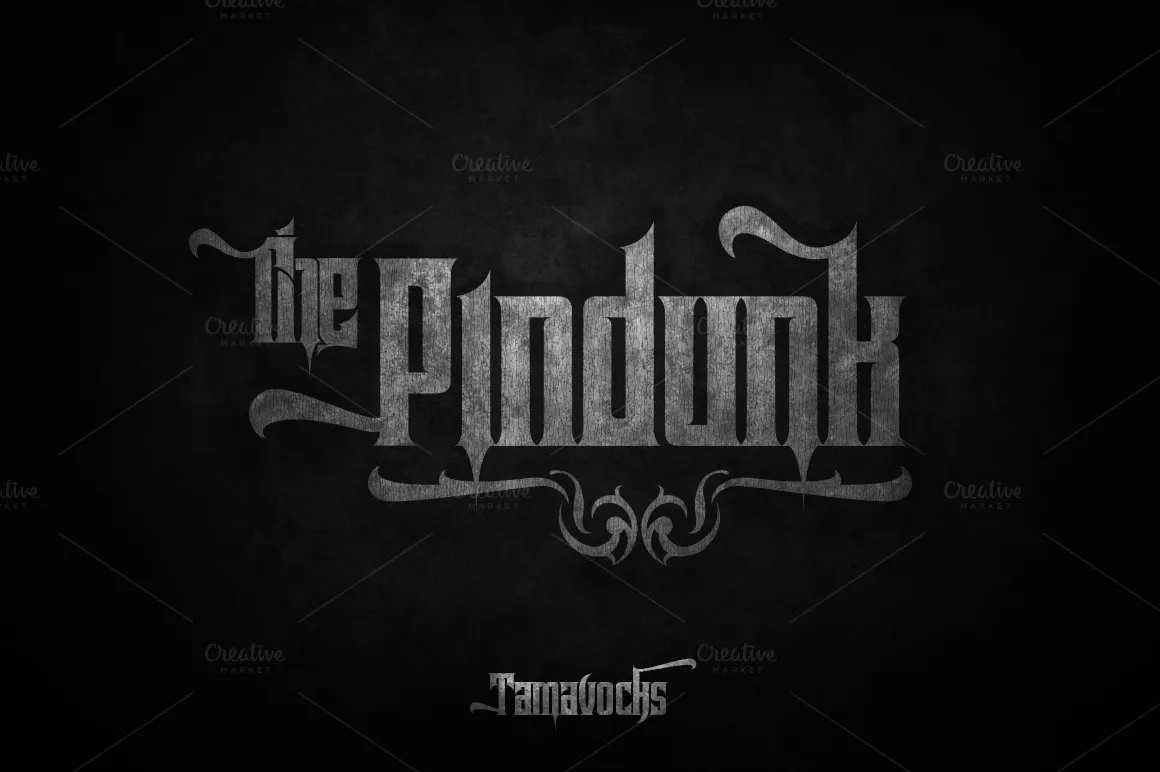
Pindunk Typeface – Download Grátis
Pindunk Typeface é uma tipografia inspirada nos estilos gótico e swash, oferecendo uma experiência visual única para os designers. Inspirado nas nuances arcaicas dos estilos góticos, esta fonte apresenta um conjunto completo de letras maiúsculas e minúsculas, além de suporte a múltiplas línguas e moedas, números, pontuações alternativas, ligaduras e alguns caracteres extras. Pindunk é uma excelente escolha para aqueles que buscam uma tipografia que combina modernidade com um toque nostálgico, tornando-a perfeita para projetos digitais ou impressos exigentes em termos de linguagem e numeração. Com sua gama completa de caracteres, Pindunk é uma fonte ideal tanto para designers profissionais quanto para iniciantes que desejam explorar o mundo fascinante da tipografia.